过去有说“字如其人”。意思是从一个人书写的字体当中,就可以不见其人,但见其颜,但闻其声,十有八九地能够从字中看出书写者的特征来。一个人如此,一个国家、一个民族亦然。那么,什么字体能够代表华夏民族的文化特征呢?我认为是宋体字。中国文化浩浩荡荡上下五千余年,有许许多多的文化积累,在汉字的发展历史长河中也出现过各种各样的字体,为什么独说宋体字是中国文化的表征呢?本文从如下几个方面对宋体字所蕴涵的中国文化的特征作一番描述。
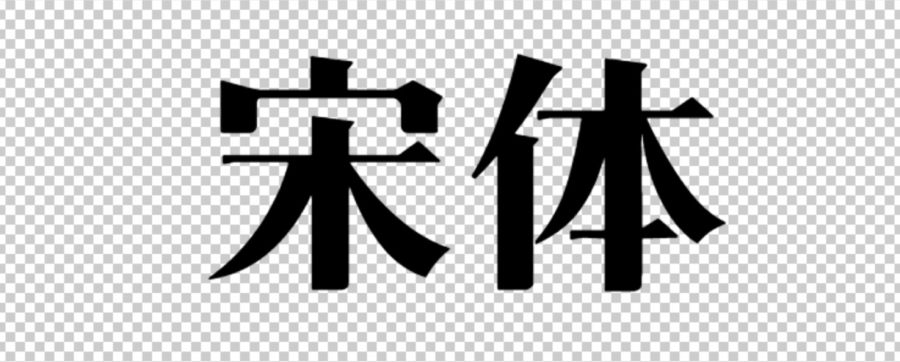
一、宋体字的二个源头
笔者认为,今天我们看到的宋体字,应当有二个源头。首先是中国的书法艺术。中国很早就出现了文字,和世界其它文字的发生一样最初都是以象形来表意的。早期的汉字是刻写在动物的骨片上和铸就在青铜器皿上,这便是甲骨文和钟鼎文,而这之前,只有刻写符号和传说的记录,没有实物佐证了。
甲骨文是殷商时代刻写在龟甲和兽骨上的卜辞。因为是刻写在形状各异的甲骨片上,刻写后也不好改动,所以先人们顺势就章,一气呵成。整体效果或规矩整齐、错落有致,或变化多姿、随意大气,体现了人类追求均衡对称、和谐稳定的天性。从中国汉字演变的发展来看,大致是这样的一个发展过程:甲骨文、金文、大篆、小篆、隶书、草、楷书至仿宋体、宋体字,这过程体现了人类追求简约明朗、均衡对称、整齐统一的程式化的总体趋向。
公元前221年,秦始皇建立了中国历史上第一个统一的中央集权制的封建国家,随即采纳丞相李斯的建议,发布了“书同文”的政令,将前各诸侯国的异笔繁杂的字体全部废除,改省大篆,设计了一种新的书体,并加以在全国推行,这就是“小篆”。现在看来,这是秦始皇高瞻远瞩最为智慧的一举,因为通过武力只是在地域版图上统一了中国,而“书同文”的统一,实是在民族心理上、文化上统一了中华民族,使得中央帝国在秦以后,尽管战争不断也好,异族统治也好,分分合合也好,都只是朝代更迭而已,最后都融入了汉字的伟大旗帜下,繁衍发展、壮大。
到了汉代,汉承秦制,中央集权制得到了进一步的发展和加强。汉武帝雄才大略,东征西伐,不断扩大中央帝国的版图,为保边疆的永安,建立了屯兵制,这屯兵制使得中国文化在边疆迅速地传播和扎根。同样也对信息传播的质量、速度、数量有了更高的要求,这时小篆又逐渐简化演变成为隶书,史称“隶变”。这种变化不仅仅是因为小篆繁杂难写,有变革的要求,其中最主要的本质原因是与中国人书写的工具毛笔的发明和普及应用有着密切的关系。是毛笔的书写形式把篆书的图画性进行了方正平直化的变革,使图画性质的汉字转向抽象化,并初步形成了构成汉字基本要素的点、横、撇、捺、竖、提、钩、折的笔划特点及方块字形的外形特征。
此外,那时的官吏有时需要快速拟写公文,书写隶书时有些笔画相互连起来,这就产生了所谓的草隶。另一方面,汉字也在向整齐方正、简约明朗的程式化方向变化,这就有了楷书。汉代已具备了中国书法中的真、草、隶、篆四种主要的书体了。
其次是第二个源头,雕版印刷术的出现。雕版印刷的发明是一个漫长的历史发展结果,它最初体现在古玺、封泥印、铭文印章和印记上。随着经济的发展,书籍产生和传播的需求加速了雕版印刷的发展和普及。
雕版印刷是将文章反字阳刻或阴刻于特制的木版上,然后用墨、纸进行拓印,这是我国的四大发明之一,其历史可追溯于唐代或更早。那时的工匠们以唐代三大书法家的楷书为临刻原本,最初是临刻,日后渐渐地加入了工匠们自己的智慧,并结合刻刀和木版材质的特点,使书法字体更加规范化,更易于刻写。
早期的雕版印刷的刻写字体,常由书法家书写楷书后由刻工们直接反拓后临刻,刻工们对书法家十分敬重,所刻字体都尽可能地保存了书法家的特点。因此,也有着浓厚的正楷书法味道。这种字就是今天我们称之为“仿宋体”的前身,也是“宋体字”前身。因之,宋体字的演变过程是通过雕版印刷技术从书法正楷到仿宋体再到宋体。但为什么产生于唐宋先于宋体字的仿宋体,会叫仿宋呢?原来这是我国进入铅活字印刷时的事情。1916年我国著名的书法家、篆刻家丁辅之和丁善之两兄弟参考北宋古刻善本仿写制作的,当时命名为“聚珍仿宋”。之后,上海华丰制模铸字所、百宋铸字印刷厂都有多种仿宋体面世。今天,仿宋体已成为我国的硬笔正字。
雕版印刷术到了二宋时期,由于当时社会安定祥和,经济发展迅速,政治开明,平民百姓亦可通过科举进入仕途,所以社会读书风气日盛,官民皆有藏书的习惯,甚至连农村中一些小康殷实的家庭也藏书千卷。雕版印刷的刻书机构更是遍布城乡,宋朝三百多年是我国雕版印刷的黄金时期,其技术也影响了东瀛诸国,更是启迪了欧陆。
由于社会对书籍的需求的增长,刻工又必须更快、更多、更好地完成任务。因此,总结了一套快速刻字的方法,在摹写楷书的基础上,充分利用刻刀的特点,对楷书进行改造加工,在用最少的刀功条件下,刻写出楷书的待征,这就形成了今天我们所称之为的宋体字。宋体字发生于唐宋,但成熟于明,所以在东邻日本称之为“明朝体”。
雕版刻工在摹写唐代楷书的过程中不知不觉地,完成了汉字程式化的伟大任务,为现代汉字印刷字体的规范化发展铺就了一条坦途。可以说,宋体字上承中国书法的精髓,下启汉字规范化,程式化的先声,并把汉字的传播速度一下子提高到了一个崭新的平台上。
宋体字的两个源头流向一处,汇聚一起形成了宋体字。因此,宋体字是与中国书法一脉相承的,是对中国书法楷书的终端释义。它非常巧妙地、合理地把中国书法楷书的本质特征用刻刀及传统印刷术的形式反映出来,并得到中华民族的认同。
二、宋体字的审美韵味
中国书法和雕版印刷的结合产生了宋体字,因此,宋体字不但有中国书法的魅力,还具有雕版印刷及木版刀刻的韵味。
1、宋体字承传了中国书法的审美韵味
中国书法艺术除了汉字本身独特的象形性、图画性特点外,独特的书写工具毛笔,是形成中国书法的最重要的原因。毛笔它柔软而富有弹性,能意地弯曲扭动,张驰有度,能潇洒自如地表现出各种粗细、大小、曲直,刚柔的线条变化。更能把书者的情感赋予其中,这种“软笔”可横、可竖、可点、可撇、可捺,形成了中国书法特有的形式特征。书者的技艺到一种高度时,毛笔在手,字已非字,点画线条随心书写,千变万化,以至所书之字似有生命的境界。
宋体字在笔画上,仍然保持了中国书法的本质特征。在与唐楷颜体比较时,我们看得更清楚,如点、捺、撇及转折处的顿挫处理,就是对书法运笔进行了高度的艺术化概括。
从汉字书写的发展来看,唐代三大家的楷书,是中国书法程式化的颠峰。楷,模范也。因此,也顺理成章地成了中国刻版印刷字的楷模。在品味和设计宋体时,追求中国书法和木版刀味、雕版印刷痕迹的韵味是十分重要的,如果没有这种感觉,那只是美术字而已。如现在的圆体,综艺体,根本没有传统书法的味道。
另外,从宋体字的角度来看,唐代三大家的楷书因追求方正和程式化,从而失去了书法艺术所需要的随心自由的激情和灵动。唐楷太程式化了,使人极易想到宋体字,实际上唐楷也就是今天的宋体字的范本,它们像个成熟而正襟危坐的长者,不愈矩,缺乏变化的勇气,因而失去了自由的偶然性。
唐三大家的楷书,虽然给后来的习字者带来了很大的便利,可说是人学人像,个个都是柳公、颜公,但却毫无个性可言,很难习得此法而成为书法家。倒是能成为入门习字和写好字的范本,但不能作想成为书法家的始终范本。学书者应直追秦、汉、魏、晋,特别是汉代书法,随心抒写、大气豪迈,如《汉简》、《泰山经石峪金刚经》等等。
唐楷是中国书法楷书的顶峰,顶峰面临的是什么?是下坡,是重新开始,唐楷也就是宋体字的起始点。
2.传统印刷与木版刀刻的痕迹韵味
今天版本学家对于宋体字下的定义是:“横平竖直,横细竖粗,起落笔有棱有角,字形方正,笔画硬挺。”起落笔的棱角,应是宋体字的最大的特征,它是雕版刻工们在长期的刻写过程中对唐楷的笔画进行归纳化处理,形成的特有的装饰化特征,是刻刀留下的韵味,它既保留了唐楷的本质特点,却又比唐楷更加方正,正刀口挺刮有力。这种刀刻的痕迹在传统印刷的过程中,因为印墨和中国纸张的特征,再加上压力,使得最后印制的的成员呈现在我们面前时,宋体字的棱角又稍稍圆润浑厚起来,十分耐看,这无意之中,把楷书的书法味和雕版的刀刻味揉和在一起,形成了宋体字的典型特征。因此,学书法要上溯秦汉,而设计宋体字却要直追唐楷和宋明的雕版刻刀味,因为,那才是宋体字的源头,唯有源头活水来。
三、宋体字的中国文化特征
宋体字源于唐宋,盛于明清,距今已有一千余年的历史,在有形的文化中,千百年来一直仍然在使用却没有太多的改变的应首推宋体字了。宋体字的形态特征和其精神特质也在无形之中影响了一代又一代中国人。
中国人从小在一个个小方格、大方格本中练习写字,老师要求要根据字体的笔画顺序把字端正、均匀居中的写在方格内,不能偏格也不能逾越方格,要在这方格内经营笔画的位置,相互谦让,安排好每笔每画,利用好每一小空间。汉字有一笔画的字,也有十几笔画的字,如“毫”和“丁”字,怎样安排好字的笔画关系及少笔画和多笔画的黑白轻重的协调问题,都须灵活对待。正是这些因素,养成了传统中国人做事规矩守信又善于经营位置的国民性。中国字的“田”字也是格子,表明被分割划分的水田,传统的中国人守在一亩三分田的格子里,精耕细作、互助互让、充分利用、以小做大、舒舒展展、游刃有余,居然也可以养活全家人。宋体字直接承传了中国书法楷书的精神,不着痕迹地把中国书法楷书转变成了印刷宋体字,并深深影响了我们的审美趣味。宋体字方正平稳,对称均衡,起伏相让的字体结构,端庄典雅,舒展大气,利用得当,追求精致的精神内涵,都无时无刻的在影响我们的行为。
宋体字的美学精神,无疑已深深地扎在我中华民族的精神气质之中,并在其发展中,不断的注入了宋、元、明、清的时代审美理想和中华民族的人文精神内涵,成为中国文化的衣裳。既然是中国文化的衣裳,我们就应该去重视它,保护它,爱惜它,发展它。但是,目前在对待宋体字的研究认识上及态度上都处于一种游离的状态,并没有在中国文化发展的战略高度去重视它、认识它。以至,出现了很多认识上和运用上的偏差。如今我们常把宋体字当成是美术字,这在专业书刊上都有如此认为,这是非常不对的。宋体字直接继承了中国书法的精髓与中国书法有着一脉相承的关系,不仅是中国文化的衣裳,而且是中国文化的正装。因此,要本正清源地指出:宋体字不是美术字,它是正本汉字。美术字是对正本汉字进行美化、装饰、加工、设计后的各种字体,按照前述对宋体字的溯源进行研究后,其正确的定位应该是:
仿宋字(早期的宋体字,现硬笔字的正字)
楷书 各种美术字
宋体字(成熟期的宋体字,印刷体的正字)
此外,仿宋体和宋体在笔画上是有所区别的。宋体字因刻刀刻写的关系,某些字某些笔画是特别设计的,因而不适合用硬笔书写,如走字旁。在日本仿宋体被称之为教科书体。这对初学汉字的小学生是非常有利的。所以,我国的小学生字典在宋体字旁应该要同时标注仿宋体。
既然宋体字是正本汉字,我们就要研究她,并给予其应有的地位。然而,我们在宋体字的研究方面明显落后于台湾、香港地区和相邻的日本,如相互比较我国目前的宋体字,我们就会发现:我国目前的宋体字整体效果不如港台,这其中有结构的问题也有字体神韵的问题。中国汉字由于笔画较多,又是象形,因之在结构处理上有很多微妙的关系。点画的布局的一点差别,都会影响到字体的整体结构,笔画的造型韵味有没有传统书法味和雕版刀刻痕迹有没有传统印刷的趣味,都会影响到宋体字的内涵,这就需要专门的人和机构去研究。当然还有汉字简化之后的某些因素,有些简化汉字没有考虑简化后的结构形式问题,如“广”和“广”简化后的广字明显留位太空,不易居中,手写时常将其撇划有意向内靠,以求平衡居中。
上世纪六十年代,我国的宋体字曾出现过一个高峰,其代表字体之一是由上海印刷技术研究所活字研究室设计。当时聘请了著名篆刻书画家钱君匋先生为顾问组织了一代优秀的老刻工、青年美术工作者和善写正楷的书法家一起组成了一支高水准的研究队伍进行攻关,完成了宋一体的设计任务,供《辞海》选用。另一代表作为上海制模一厂为《毛泽东选集》专门设计的宋二体。当时这都是头等的政治任务,国家非常重视,倾力为之。但今天,宋体字的设计任务早已商业化,字体的研究都是由民间企业去完成。由于在文化上没有宏观的战略思想,加上文革时期的文化断层和今日的专业设计人员不屑于字体设计的工作,所以,现在的宋体字明显地缺乏中国传统文化的精神内涵。在宋体字的使用上,今天各种美术字层出不穷,使用者不明,设计师也是盲目跟风。没有一个准确的把握,很多需要用宋体字来表现中国文化端庄典雅、舒展大气的地方,却用了当下所谓时髦的字体,如政府的牌匾、信函、台头用综艺体。再如中国的国酒茅台酒,“贵州茅台酒”几个字根本没有中国传统文化的韵味,更没有中国酒文化的味道,酒厂的标准字居然也是采用最没中国文化品味的综艺体。最近,香港地区发行的新10元纸币的设计用的是圆体,拿在手中花花哨哨,完全没有权威感,与原有的百元、千元纸钞的设计相去甚远。要改变当下我国宋体字发展的困境,应该:
1.进一步明确宋体字不是美术字,而是中国文化的表征,是中国书法的继承者,是正本汉字。只有秉承这样的认识,才能把宋体字的研究推向一个新的高度。
2.宋体字既然是中国文化的表征,就应该把宋体字纳入国家文化发展的总体战略中去,以国家的行为去研究它。在此建议成立“国家字体研究所”专门对此进行研究,如在法国就有专门从事字体研究的机构—“法国国家字体研究室”。作为正本汉字宋体字,在使用的过程中,也会随着时代的审美的变化而变化,如字体的粗细变化,宽扁变化,字体结构的松紧变化,笔画转折线脚的微妙变化,等等。日本人对此有非常深入的研究。因此,我们要研究宋体字的时代审美特点,与时俱进,隔若干年发布数套宋体字,引领汉字圈的潮流。
3.给予宋体字明确的地位。如“国家字体研究所”推出的宋体字,可称为“国宋”。可以以序号命名“国宋1号”、“国宋2号”,或以风格命名“国宋典雅”、“国宋商务”,或以推出的年代命名“国宋2005”等等。这些字体有适合政府机构的,也有适合出版部门的,还有适合商务使用的。
千百余年来,外来文化一直冲击着中国传统文化,虽然中国文化有着巨大的包容性,但也应警惕在这包容的同时,会不知不觉地改变许多自己应固守的东西。今天我们已很少着唐装了,也不拱手抱拳行礼了,而相邻的日本却仍旧鞠躬行礼,仍旧保留着和服并研究发扬着和服。中国的传统认为“德发至于内,礼形于外”,会见宾朋好友时,理应整衫齐容。当我们把方正大气、儒雅精致的宋体字呈现在人们面前时,这就是施人于礼了。今日,我们的国家日益昌盛,是中华民族发展的最好时机,经济要发展,文化更要发展,作为中国文化的表征——宋体字,更要常新、常靓,引领汉字文化的流向。